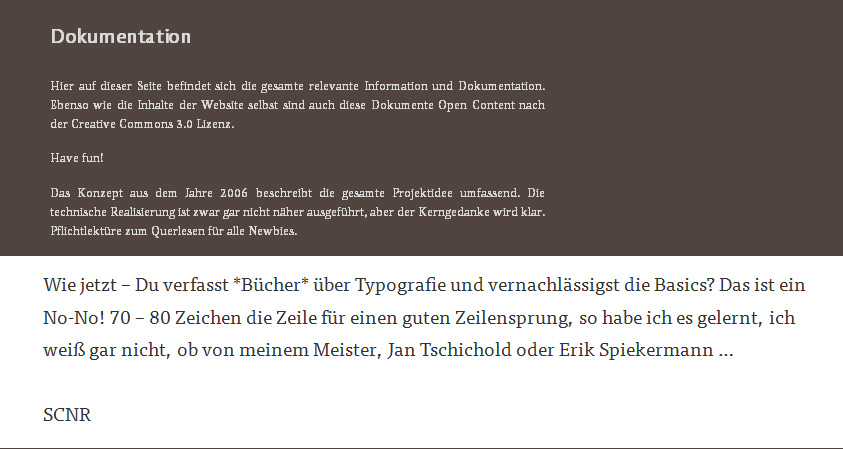
Was können wir tun im Forum in Sachen Typo?
Also, zunächst ja wohl einmal ordentlich schreiben. »Think before you type!« war schon im Usenet eine gute Idee. In einem Typografieforum sollten einwandfreie Orthografie, Interpunktion und Grammatik eigentlich selbstverständlich sein. Sind sie aber leider nicht.
Aber was können wir tun, wenn uns doch hier im Forum kein InDesign bzgl. Formatierung von Beiträgen zur Verfügung steht? – Nun, das Allernotwendigste, ich habe mir in dieser Richtung schon seit Längerem Gedanken gemacht.
Ein Gedankenstrich (Alt- - am Mac, Windows weiß ich nicht) ist kein Divis und sollte mit Bedacht eingesetzt werden, nämlich dann, wenn es darum geht, einmal kurz innezuhalten in seinem Redeschwall …
Leerzeilen! Das verbessert die Lesbarkeit doch auch und sieht erheblich eleganter aus als dieses Gequetsche mancher Leute hier.
Sonderzeichen & Umlaute: Alles kein Problem mehr seit UTF-8. Nur Mut! Es gilt, dieses Medium zu emanzipieren, zu befreien von seinen frühen grobmotorischen Anfängen! ASCII ist tot!
Emoticons: Grundsätzlich ja, aber bitte mit etwas Zurückhaltung, sonst wird’s* albern …
Ein Auslassungszeichen setzt man am Mac mit gedrückter Alt-Taste und dem Punkt, Windows entsprechend: …
* Man beachte den Apostroph! Das ist weder ein Zollzeichen noch ein Hochkomma.
Sorry, aber Sonderzeichen sind auf Windoof-Rechner noch immer ein
Problem. Für den langen Gedankenstrich muss man beispielsweise Alt+0150 (auf dem Nummernblock) eingeben. Auf Laptops ohne Nummernblock mus man den dazu oft über Fn + Num erst einblenden, und hinterher ausblenden. Und wer her auf Tabletts oder Handys antwortet, ist ganz arm dran.    Auch das Auslasungszeichen … habe ich mir selbst erst durch einen eigens modifizierten Tastaturtreiber auf's Klapperbrett geholt.
Mag sein, das eine T2-Tastatur hier für Abhilfe sorgt, aber die gibt es derzeit nur recht teuer von nur einem Hesteller. und auf Laptops gleich gar nicht.
Einen Windows-Tastaturtreiber welcher im wesentlichen dem T2-Standard entspricht kann man sich hier herunterladen. Das funktioniert bei mir mit einer ganz normalen Tastatur und ist wohl auch auf Klapprechner-Tastaturen machbar. Es fehlt halt die Gravur der Sonderzeichen auf den Tasten. Da man aber ohnehin nicht aller Zeichen benötigt, wenn man nicht gerade mit zig Fremdsprachen arbeitet, kann man sich die benötigten Zeichen merken oder auch einen Zettel an den Monitorrand pappen.
Allerdings habe ich mir eine kleine Änderung mit Hilfe des „Microsoft Keyboard Layout Creators“ erstellt. Auf die Tasten „AltGr + X“ und „AltGr + V“ habe ich mir die normalen Anführungszeichen „Gänsefüßchen“ gelegt (sehr nützlich in CorelDraw) und die von mir wenig benötigten »Chevrons« liegen nun auf „AltGr + d“ und danach „X“ bzw. „V“. Im Originaltreiber ist dies umgekehrt.
Alles richtig; aber eigentlich spreche ich in einem Forum – ich schreibe nicht, und schon gar nicht setze ich – und Sprechen ist formal viel weniger stark geregelt als Setzen.
Das heißt, dass ich mir zwar die Zeichen und Regeln bereit lege und diese auch verwende, aber nur soweit wie es mir inhaltlich und ästhetisch notwendig erscheint, abwägend gegen den zu betreibenden Aufwand und die zur Verfügung stehende Zeit und Technik im Moment des Tippens des Beitrages. Und das ganz ohne schlechtes Gewissen oder Entschuldigung.
(Sollte unser Forum mal in Buchform erscheinen, hoffe ich, dass der Setzer unsere ortho-typografischen Fehler stillschweigend korrigieren wird, wie er es für richtig hält, oder ein unverfälschtes Faksimile erstellt, um das typgrafische Grauen, das hier herrscht, so richtig transportieren zu können.)
@ lars, nichts für ungut, aber vielleicht sollte man erst mit eigener seite anfangen?
der claim neben dem logo in falschen italics, ist auf einer seite wie dieser, nicht akzeptabel.
'Man' könnte - zusätzlich zu einem neuen Absatz
mit Leerzeile - auch kürzere Zeilen schreiben.
Ein Druck auf die Enter-Taste ist keine Arbeit und
erhöht die Lesbarkeit ungemein.
Oder man bittet den Forumbetrieber, das gleich von Haus aus anders einzustellen. ;-)
Im Nachhinein geht das aber nicht, da sonst die bereits erstellten manuellen Leerzeilen zu riesigen Lücken führen würden.
Dem Vorschlag mit den kürzeren Zeilen kann ich mich auch nicht anschließen. Auf Webseiten gibt es einfach keine feste Darstellungsbreite und Texte sollte daher von allein und passend zum benutzten Gerät umbrechen. Greift man da manuell ein, fällt alles auseinander, wenn der Betrag z.B. auf dem Telefon angeschaut wird.
Aber als Seitenbetreiber kann man doch schon einiges tun, um auf großen Geräten überlange Zeilen zu vermeiden, ohne Telefonbenutzer zu beeinträchtigen. Wie wärs mit
max-width: 40em
oder etwas in der Art?
Meine Augäpfel bewege ich mit besonders großer Sportivität, dafür bin ich berühmt und werde gar beneidet um die außergewöhnlich eleganten, slalomartigen Rechts-Links-Schwünge meiner Augäpfel. Das gebe ich, ein wenig unbescheiden, zu.